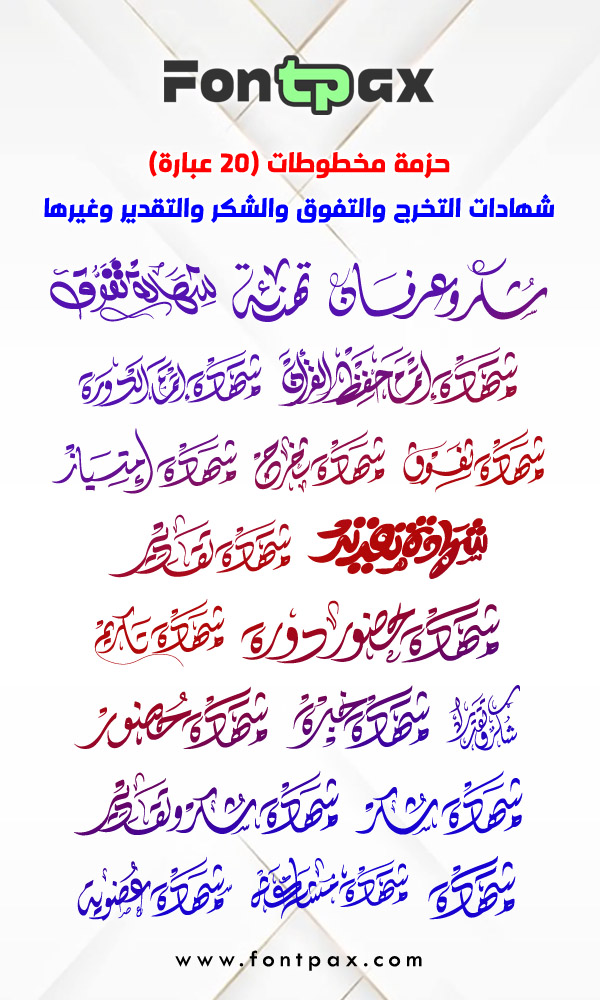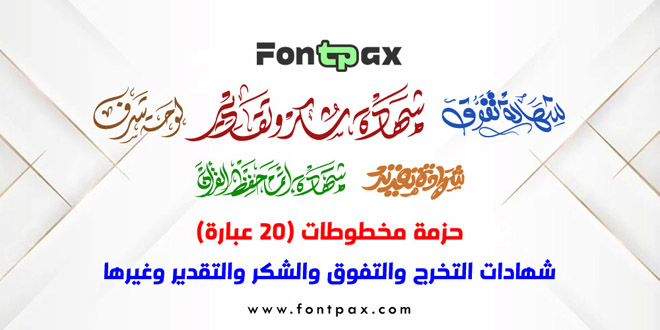
حزمة مخطوطات (20 عبارة) شهادات التخرج والتفوق والشكر والتقدير وغيرها .. حزمة تحتوي على (20) مخطوطة عن التفوق والنجاح والشكر والتقدير والعرفان يمكن استخدامها في التعليم والدعاية والإعلان والهدايا، والخط يكتب بالحروف الإنجليزية الصغيرة، متاحة للتحميل المجاني الآن.
Certificates of thanks and appreciation